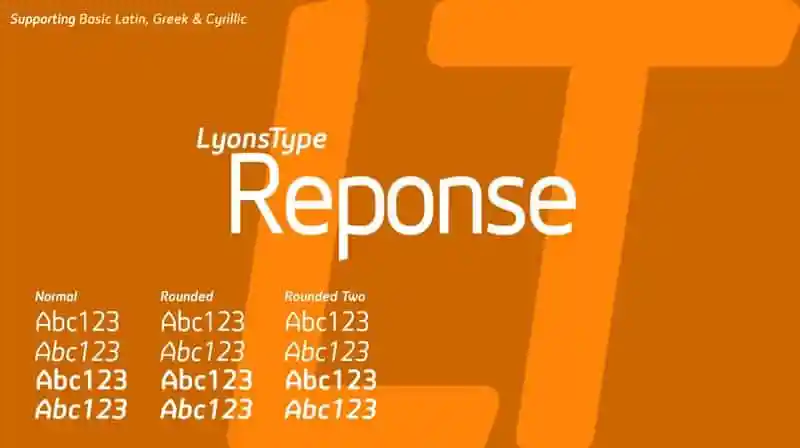
A LT Reponse Sans Serif é uma linda escolha para projetos modernos que valorizam cleanza e simplicidade. Composta por tipografia gíria com aparência alegre, essa fonte permite ao designer adicionar um toque de personalidade às suas criações. Com duas variações, cada uma oferecendo diferentes graus de arredondamento, Reponse está equipado para representar com elegância o sleekness e o aspecto futurista que tanto deseja. Ela foi criada por Daniel Lyons através do 99designs, um importante lugar de compartilhamento de ideias. Reposta é uma opção ideal para designers em busca de uma tipografia moderna que se destaca de maneira elegante e moderna, capaz de traduzir seus projetos num olhar futurista. Combinar Reponse com outros tipos de fonte pode resultar em uma composição ainda mais atraente e inovadora.